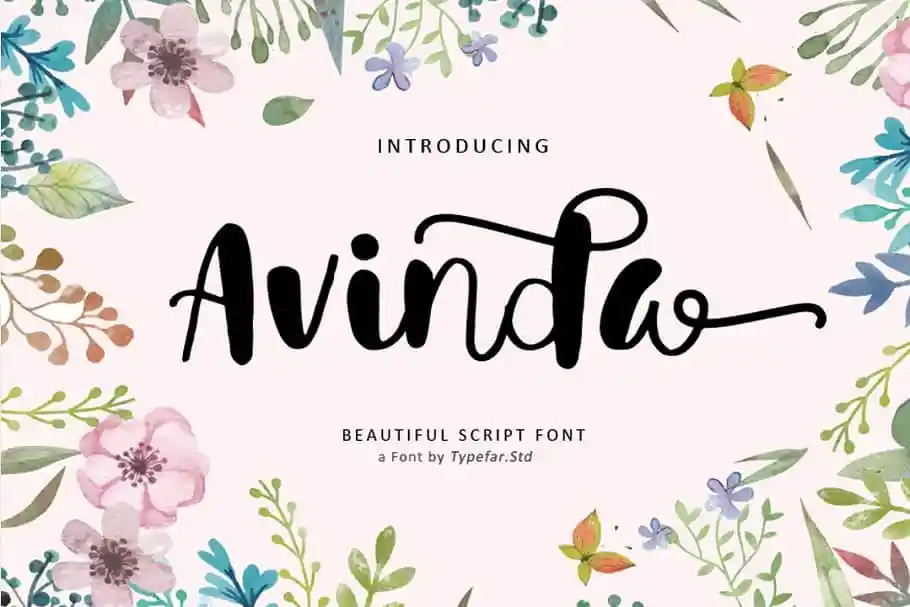
Avinda Script Font – Download Grátis
A Avinda Script Font é uma nova escolha para designers digitais apaixonados por letra cursiva. Introduzida com estilo moderno e fresco, ela traz a essência natural e elegante de um tipo script sem deixar de ser atemporal e sofisticada. Esta fonte perfeita para projetos variados como mercadorias, logotipos, convites, frases de citações, posts nas redes sociais, capas de revistas e até mesmo marcas d’água – oferecendo inúmeras possibilidades de uso criativo. Englobando uma ampla gama de aplicabilidades, a Avinda Font está disponível para todos os projetos digitais que buscam um toque sofisticado e único na sua composição visual.